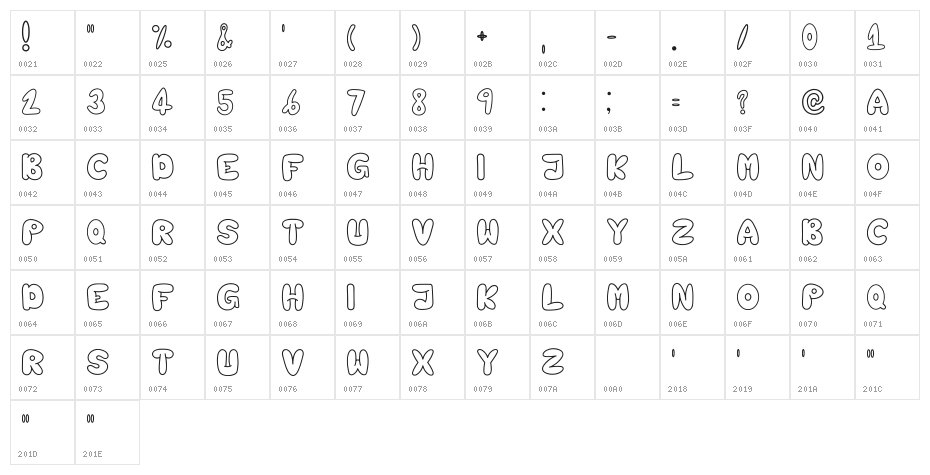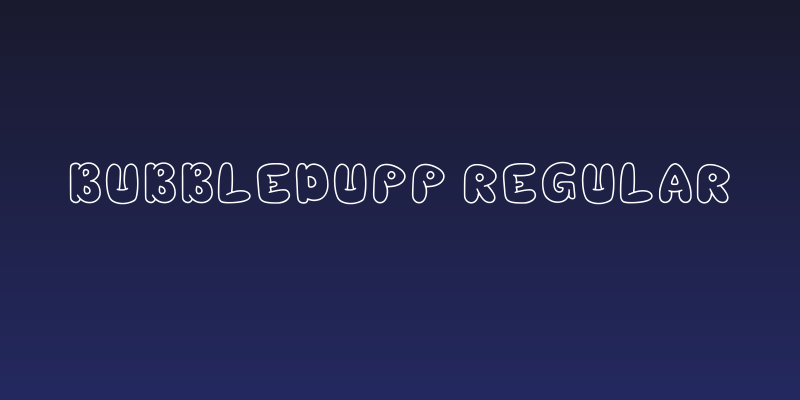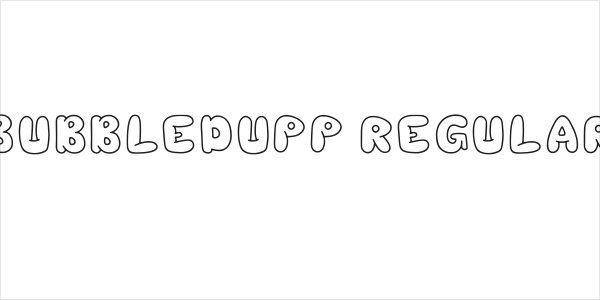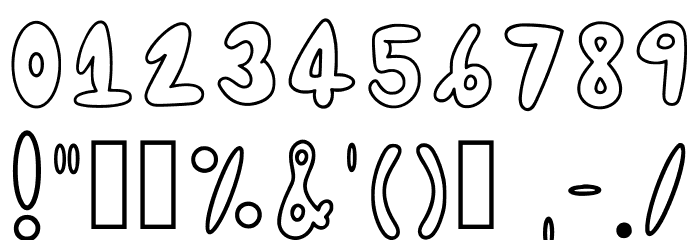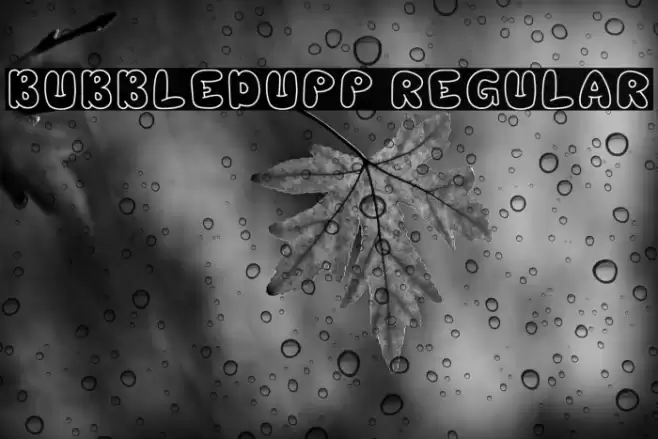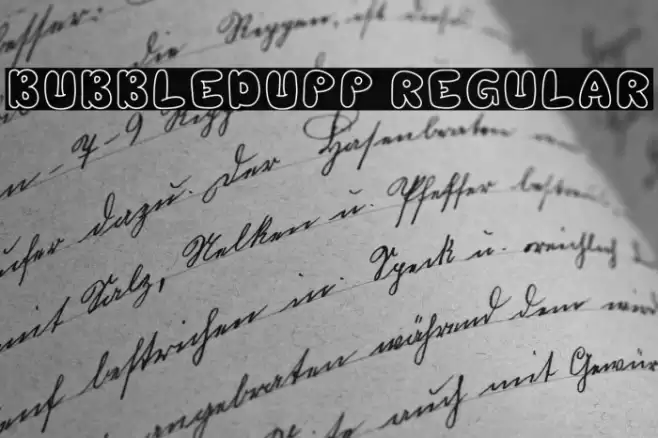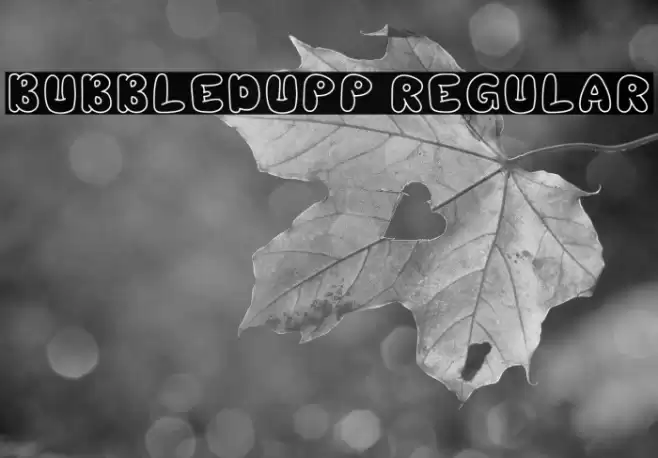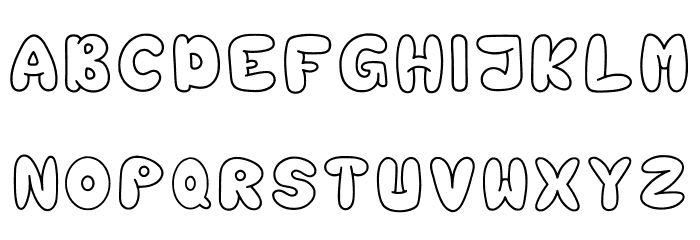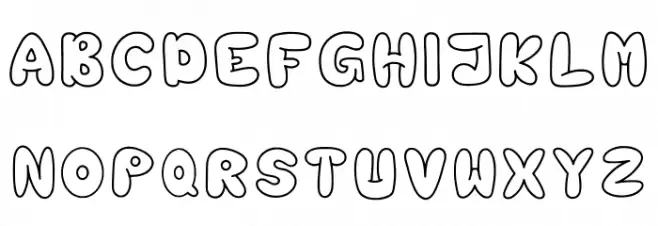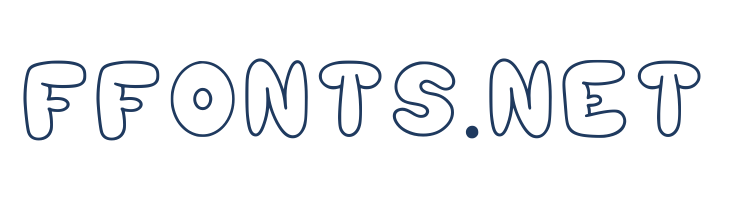
Bubbledupp Regular Font
Fonts by Marina Sanders
| Famiglia di caratteri | Bubbledupp |
| Categorie | Cartoon |
| Progetti proposti | Ideal for children's books, party invitations, playful branding, and casual social media graphics. |
| Autore | Fonts by Marina Sanders |